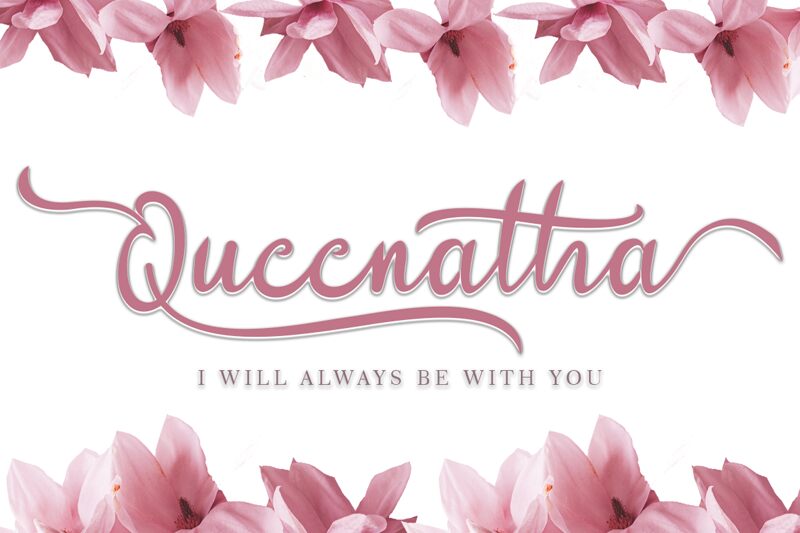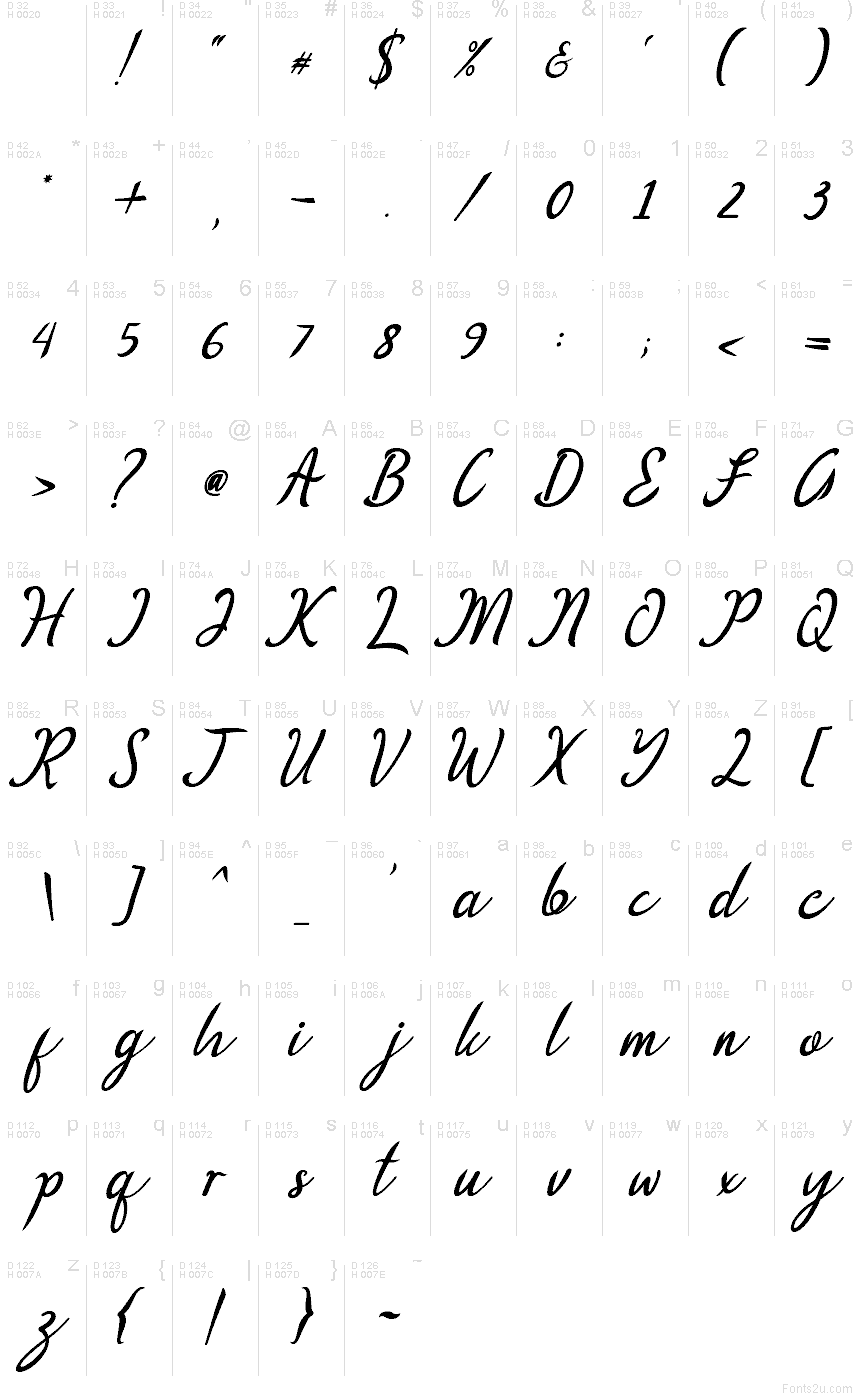
Queenatha Italic
Queenatha Italic od Yogaletter je bezplatné ručne písané písmo s plynulými spojmi a dlhými, ladnými krivkami, ktoré dodávajú písmenám jemný a osobitý rytmus. Vďaka skloneným tvarom a slučkovým ťahom pôsobí text živo a ľahko, bez toho, aby pritom stratil svoju pevnú kaligrafickú štruktúru.
Queenatha Italic sa skvele hodí na svadobné oznámenia, logá, branding butikov, grafiku s citátmi, papiernictvo či záhlavia na sociálnych sieťach. Toto bezplatné písmo dodá ručne písaný nádych projektom, ktoré si vyžadujú vycibrený štýl s dostatkom dynamiky pre blahoželania, štítky aj dekoratívne nadpisy.